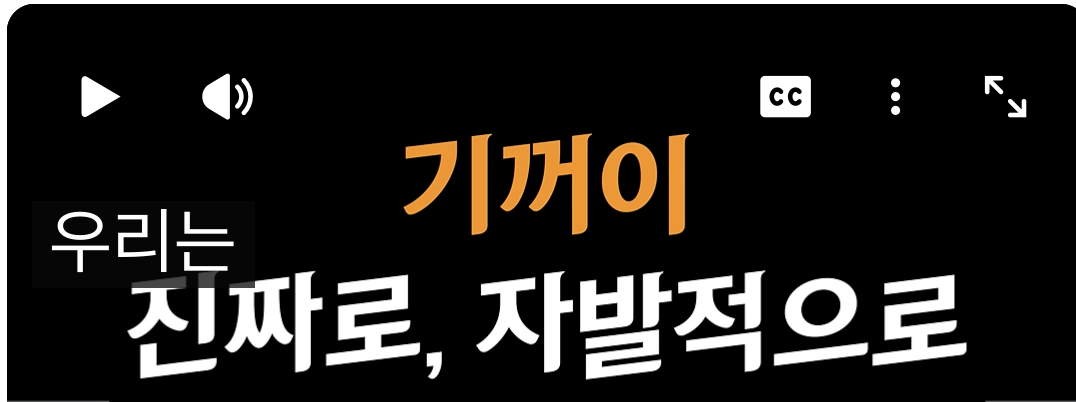
이 서체 아시는 분 계실까요? mac*** 2025.10.27 요즘 숏츠에서 많이 나오던데요, 이 서체 아시는 분 계실까요? 댓글 0 등록 sta*** DW임팩타민체 같네요 추가로 기울기를 적용한 것 같아요 https://www.sandollcloud.com/free-font/16681/DWImpactamin 2025-10-28 답글 달기 mac*** 감사합니다!! 2025-10-28 답글 달기 댓글 더보기 쉽고 빠르게 가장 비슷한 폰트를 알고 싶다면? 이미지로 검색하기
DW임팩타민체 같네요 추가로 기울기를 적용한 것 같아요 https://www.sandollcloud.com/free-font/16681/DWImpactamin